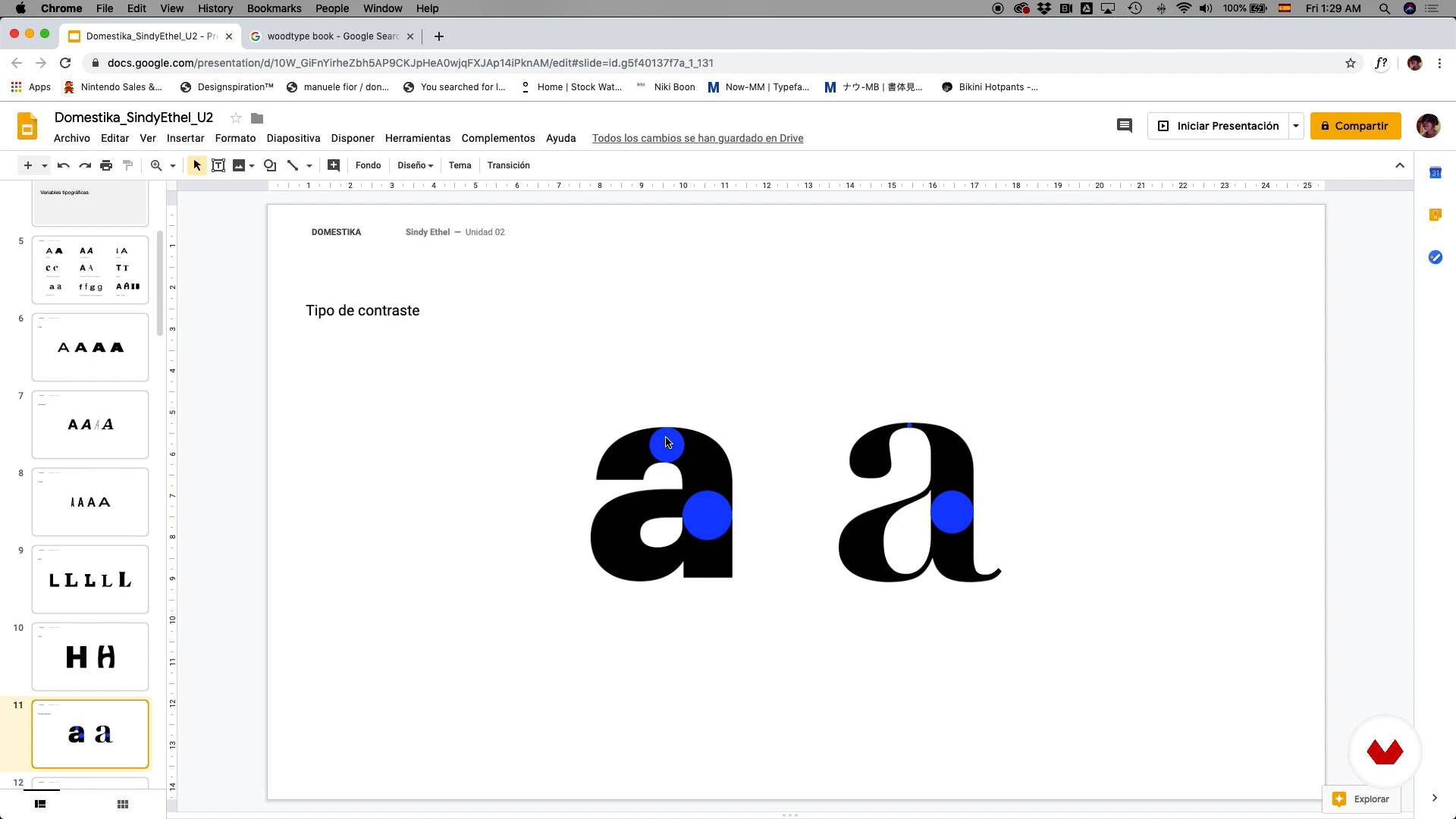
“Le lettere prendono la loro forma a causa di determinate variabili e ora ne vedremo alcune. Ti parlerò delle parti delle lettere e dei tipi di espansione e contrasto di traduzione, in cosa consistono e le differenze tra i due.”
In questa videolezione, Sindy Ethel tratta il tema Nozioni di base sulla tipografia, che fa parte del corso online di Domestika Lettering digitale per principianti. Impara a disegnare lettere con stile utilizzando Adobe Photoshop e Illustrator.
“Unità 2 Nozioni di base sulla tipografia In questa lezione esamineremo alcune basi della tipografia. questo ti servirà molto quando farai le tue lettere. Vedremo le parti delle lettere, quali sono le variabili tipografiche e cos'è il contrasto tipografico. Comprendere questa teoria ti aiuterà molto quando disegni le lettere. Vediamolo. Ci sono molte cose di cui parlerò. Il primo riguarda l'anatomia delle lettere o parti delle lettere. Proprio come il corpo umano Ha una testa, ha le braccia, ha le mani, anche le lettere hanno parti e queste parti hanno nomi. Per il corso, non hai davvero bis...”